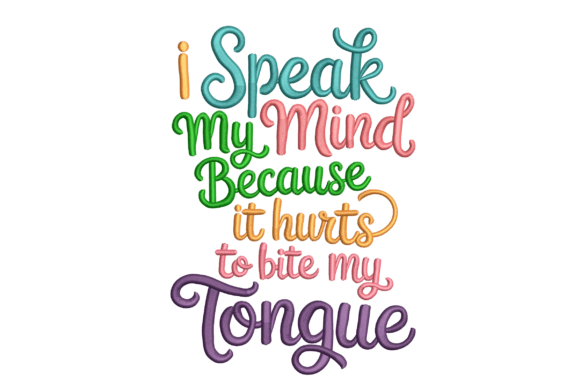
I Speak My Mind
Die richtigen Designelemente zu finden, kann eine Herausforderung sein, aber I Speak My Mind bietet eine außergewöhnliche Sammlung, die Ihre Arbeit sofort aufwertet.